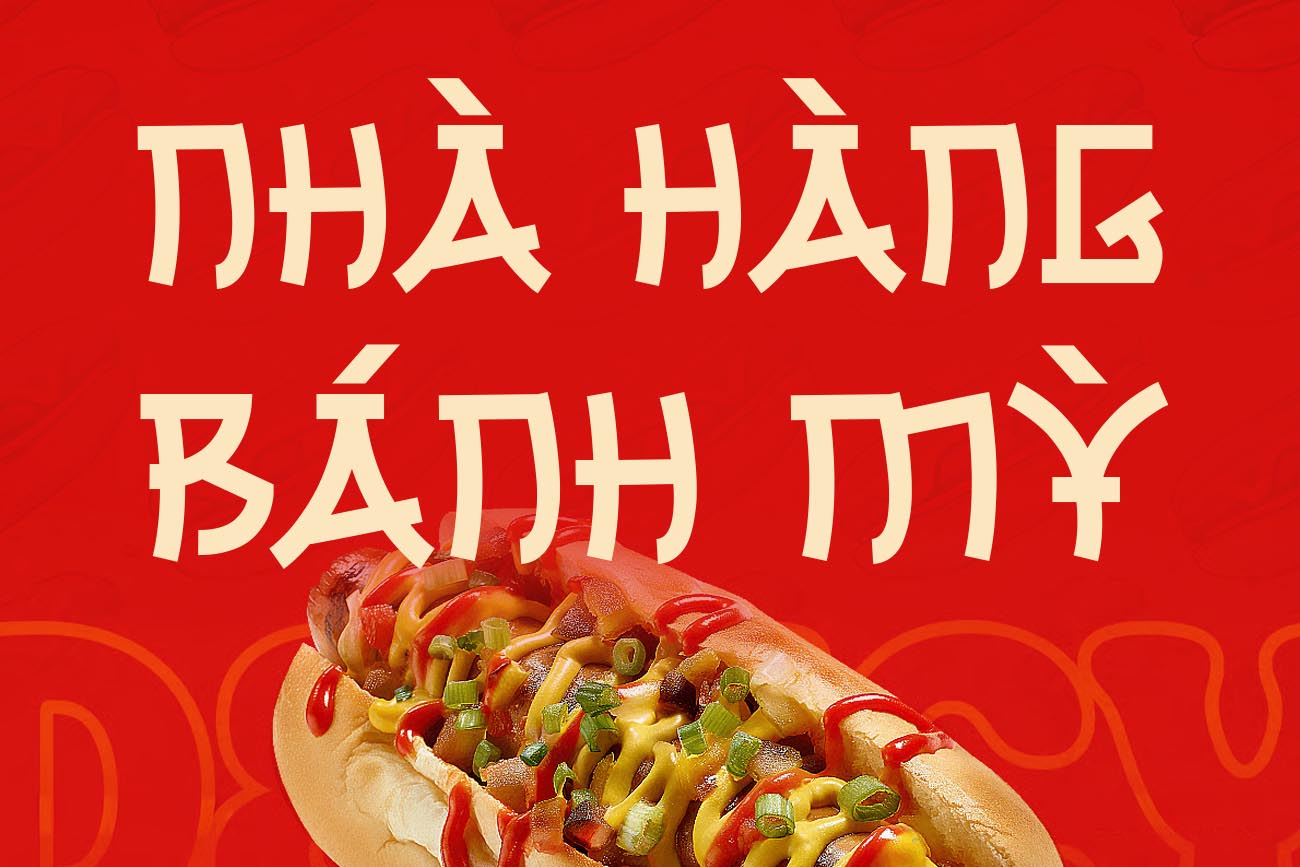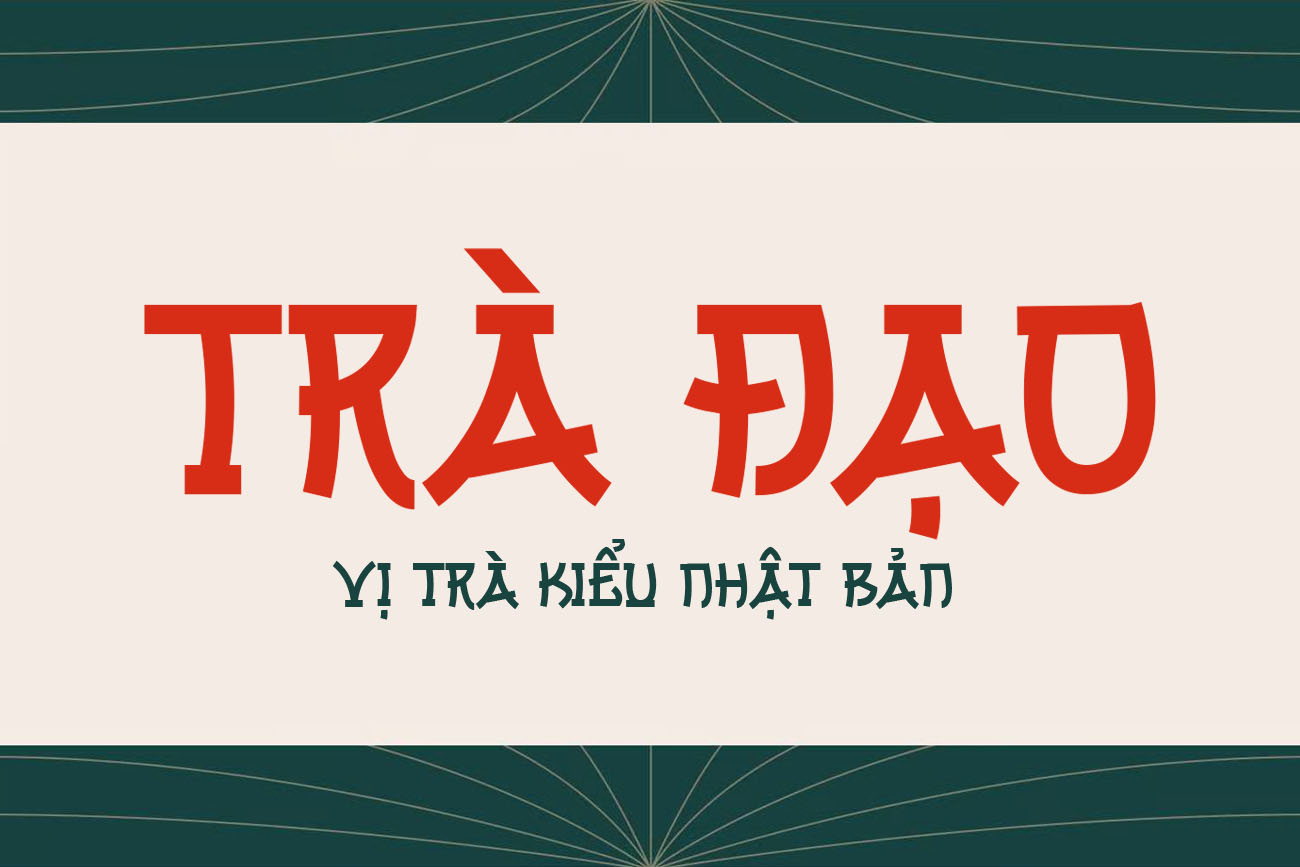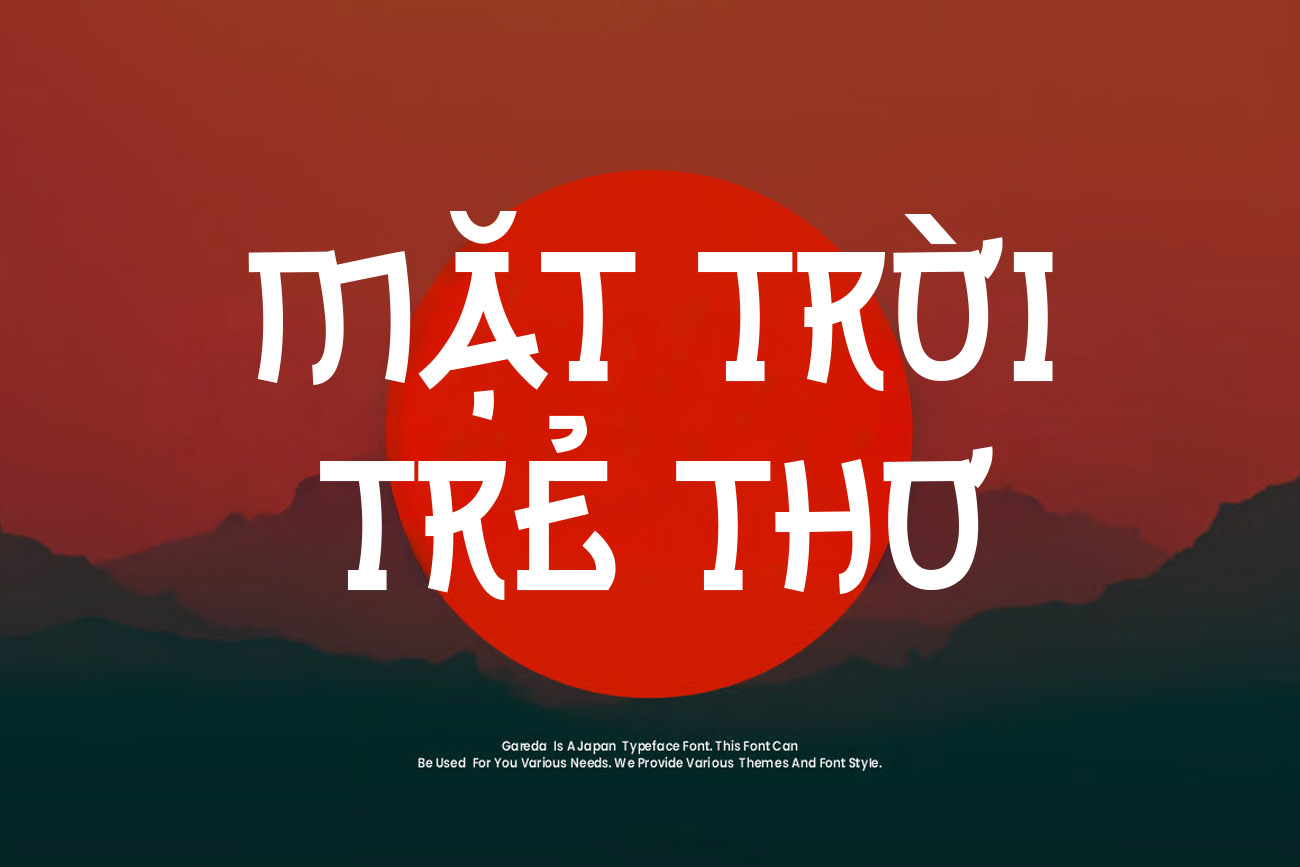
Font Chữ Đậm Chất Nhật Bản TH Gareda Việt Hóa
Trong thế giới thiết kế đồ họa hiện đại, việc tìm kiếm những typeface mang đậm bản sắc văn hóa Á Đông luôn là một thử thách thú vị đối với các Designer. Hôm nay, chúng tôi xin giới thiệu đến bạn bộ phông chữ TH Gareda, một phiên bản Việt hóa hoàn hảo từ tác phẩm gốc Gareda của Iqsiart studio. Đây là sự lựa chọn không thể bỏ qua nếu bạn đang theo đuổi phong cách thiết kế mang hơi thở xứ sở hoa anh đào.
Vẻ đẹp độc đáo của Gareda
Gareda nguyên bản là một typeface được thiết kế dựa trên cảm hứng từ nghệ thuật thư pháp Nhật Bản. Điểm đặc biệt của bộ phông chữ này nằm ở cách mô phỏng các nét cọ (brush) tự nhiên: vừa phóng khoáng, mạnh mẽ nhưng cũng đầy tinh tế và mềm mại. Mặc dù sử dụng bảng chữ cái Latin, nhưng Gareda lại gợi lên hình ảnh của những ký tự Kanji truyền thống, tạo nên một font chữ nhật bản giả lập vô cùng ấn tượng.
Với các đường nét đậm nhạt linh hoạt và kết cấu ký tự độc đáo, Gareda cực kỳ phù hợp cho các tiêu đề lớn, logo thương hiệu hoặc các ấn phẩm cần sự nổi bật về mặt thị giác.
Tại sao nên chọn phiên bản Việt hóa TH Gareda?
Mặc dù bản gốc rất đẹp, nhưng rào cản lớn nhất đối với Designer Việt Nam chính là việc thiếu hỗ trợ dấu câu. Hiểu được nhu cầu đó, Team TH đã thực hiện chuyển ngữ và cho ra đời bản font chữ Việt hóa TH Gareda.
Team TH đã rất khéo léo trong việc xử lý các dấu tiếng Việt (accents). Các dấu mũ, dấu ngã, dấu huyền... được thiết kế đồng bộ với phong cách brush của font gốc, đảm bảo tính thẩm mỹ tổng thể không bị phá vỡ. Nhờ đó, bạn có thể thoải mái sáng tạo nội dung tiếng Việt mà không lo bị lỗi font hay bố cục rời rạc.
Ứng dụng thực tế trong thiết kế
TH Gareda là một font chữ du lịch lý tưởng. Nó có khả năng truyền tải cảm xúc mạnh mẽ, gợi nhớ về văn hóa và ẩm thực. Bạn có thể ứng dụng typeface này trong:
•  Thiết kế Poster, Banner quảng bá tour du lịch Nhật Bản hoặc các lễ hội văn hóa.
•  Menu nhà hàng, quán ăn mang phong cách Á Đông.
•  Bao bì sản phẩm (Packaging) cho các mặt hàng thủ công, trà đạo hoặc thực phẩm nhập khẩu.
•  Logo và nhận diện thương hiệu cho các doanh nghiệp muốn tạo dấu ấn truyền thống pha lẫn hiện đại.